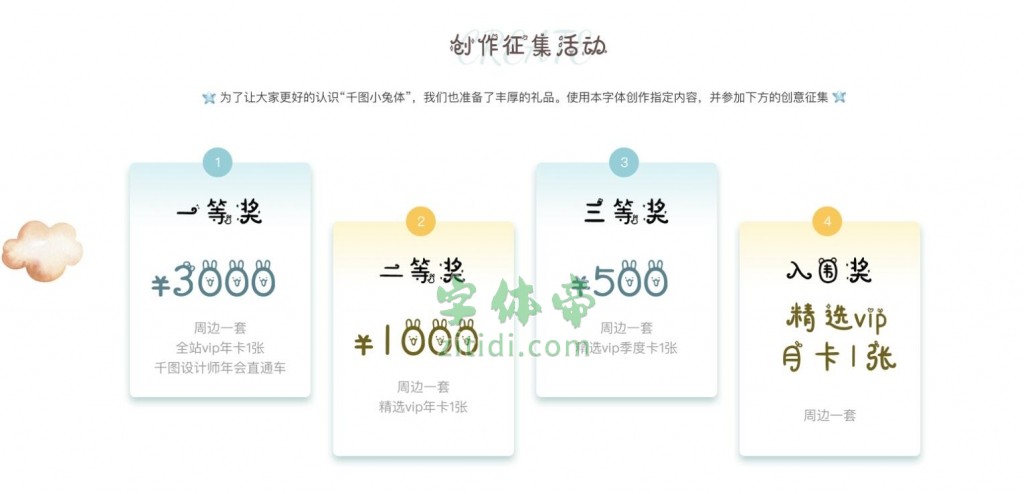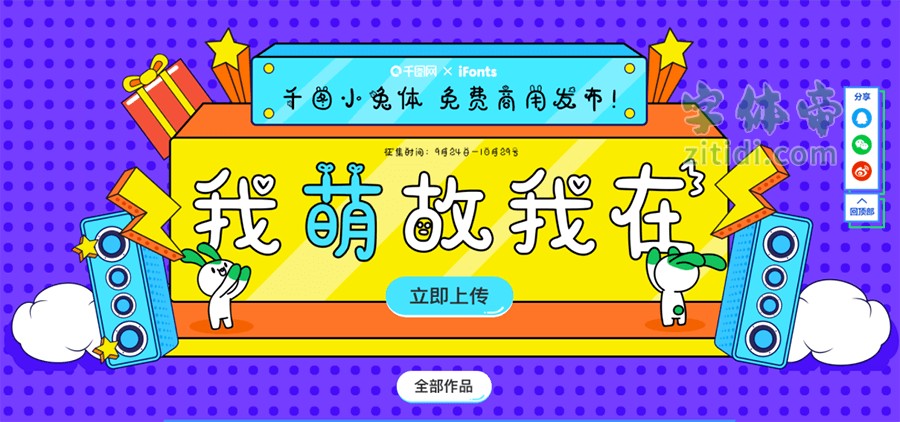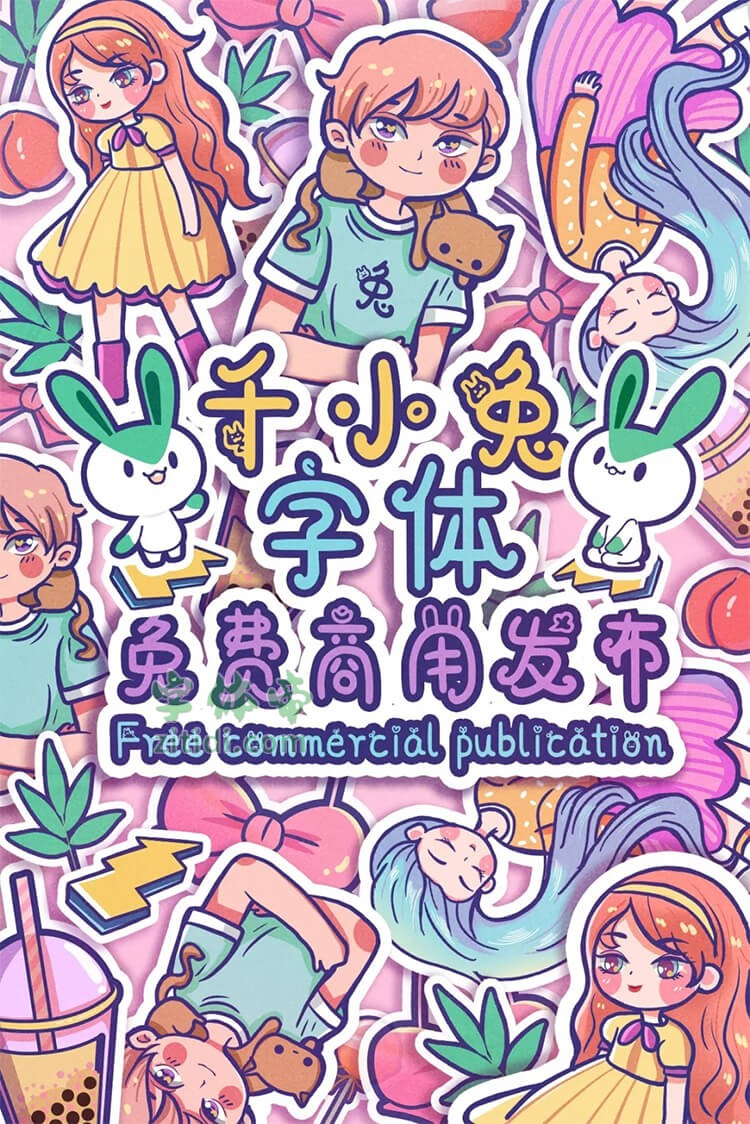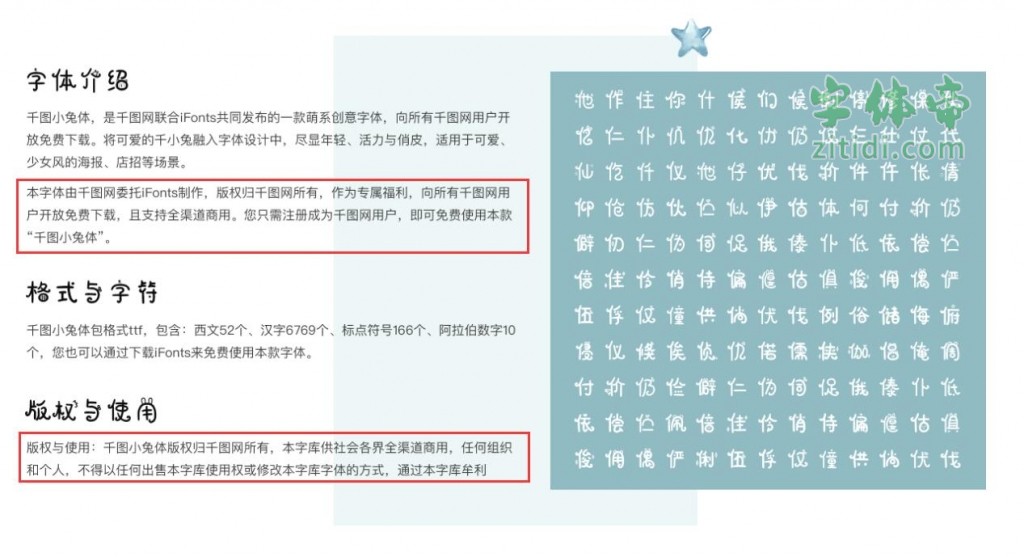
千图小兔体是千图网联合国内专业字体设计机构iFonts共同发布的一款萌系创意字体,历时半年多悉心打磨完成。向所有千图网用户开放免费下载。将可爱的千小兔融入字体设计中,尽显年轻、活力与俏皮,适用于可爱、少女风的海报、店招等场景。
“千图小兔体”是一款书写很新颖的字体,字体大方,适合各种设计作品使用!欢迎下载!